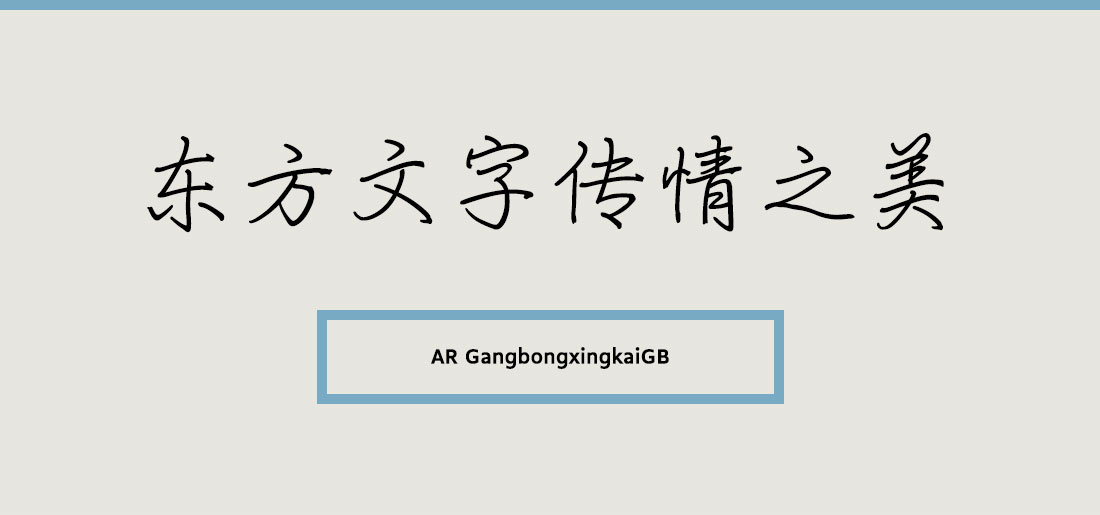
- GangbingxingkaiGB는 중국의 유명한 서예가에 의해 쓰여진 매우 희귀한 스타일의 폰트다.전통적인 서체와 비교해 볼 때에도 더 개인화되고 선명하다는 특징을 갖고 있다.폰트명 뒤에 붙은 GB라는 표기는 간체의 문자코드를 뜻한다. 간체란 중국에서 주로 사용하며 필획을 줄이고 자형을 간단하게 만든 한자다. 대만, 홍콩, 마카오 등에서 사용하는 번체(B5)와는 달라 잘못 적용할 경우 글립이 제대로 표기되지 않거나 다른 글립으로 표기되는 문제가 발생할 수 있다.
폰트 정보 구분 명조 출시년도 1986